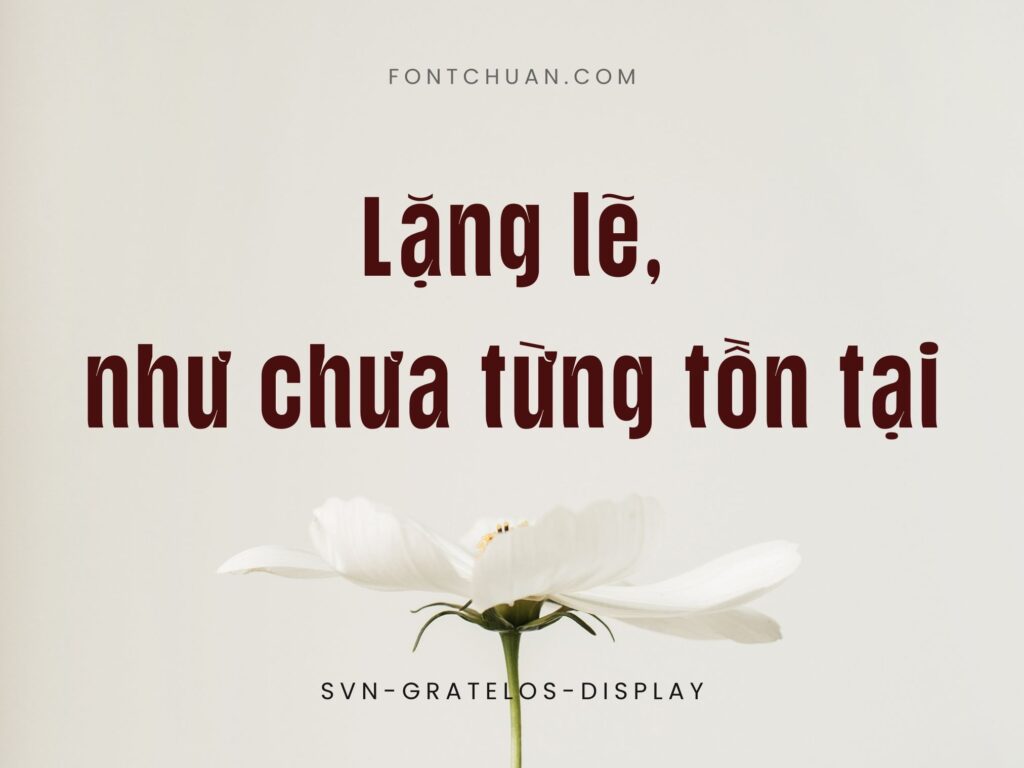
Font SVN Gratelos Display Việt Hóa
Tác giả Font: Maulana Creative
Font SVN Gratelos Display là phiên bản Việt hóa của kiểu chữ Gratelos Display, được thực hiện bởi Styleno.1 Fonts. Gratelos Display là một kiểu chữ sans-serif đậm nét và cô đọng, nổi bật với sự kết hợp giữa phong cách cổ điển và hiện đại, tạo cảm giác mạnh mẽ và thu hút. Font này bao gồm các chữ in hoa, chữ số và dấu câu, hỗ trợ hơn 100 ngôn ngữ, thích hợp cho nhiều mục đích sử dụng khác nhau như thiết kế logo, tiêu đề và bao bì sản phẩm.
SVN Gratelos Display lý tưởng cho các dự án thiết kế yêu cầu sự nổi bật và cá tính, như thiết kế logo, tiêu đề, bao bì sản phẩm và các ấn phẩm quảng cáo. Các ngành nghề như quảng cáo, công nghệ và bất động sản có thể tận dụng font này để tạo điểm nhấn trong thiết kế. Ngoài ra, font cũng thích hợp cho các sự kiện như Tết, Giáng sinh, Valentine và các lễ hội khác.